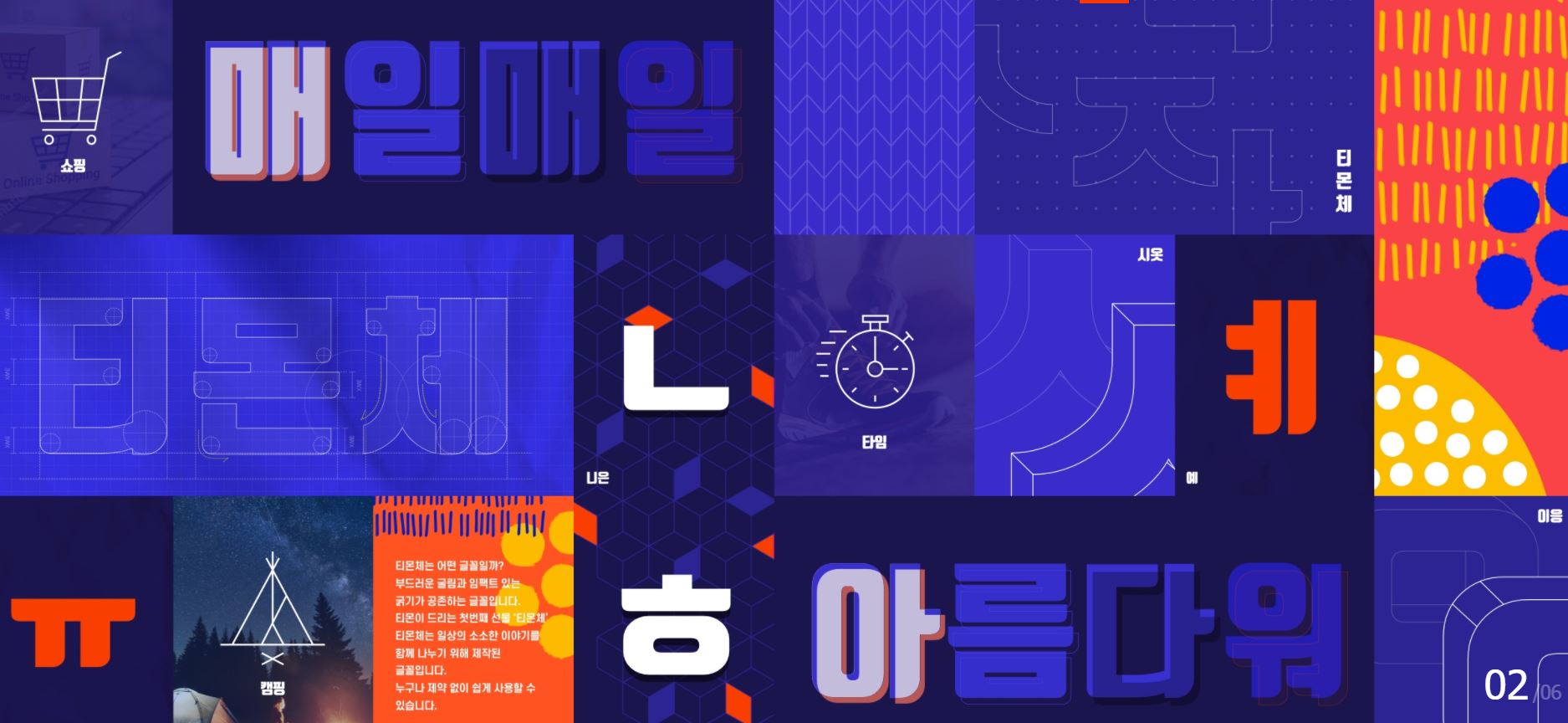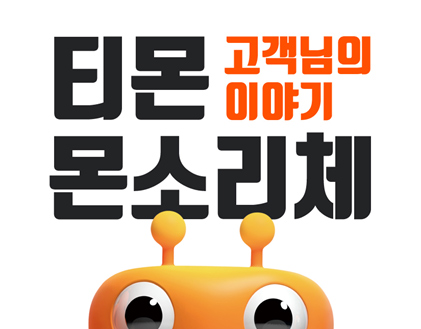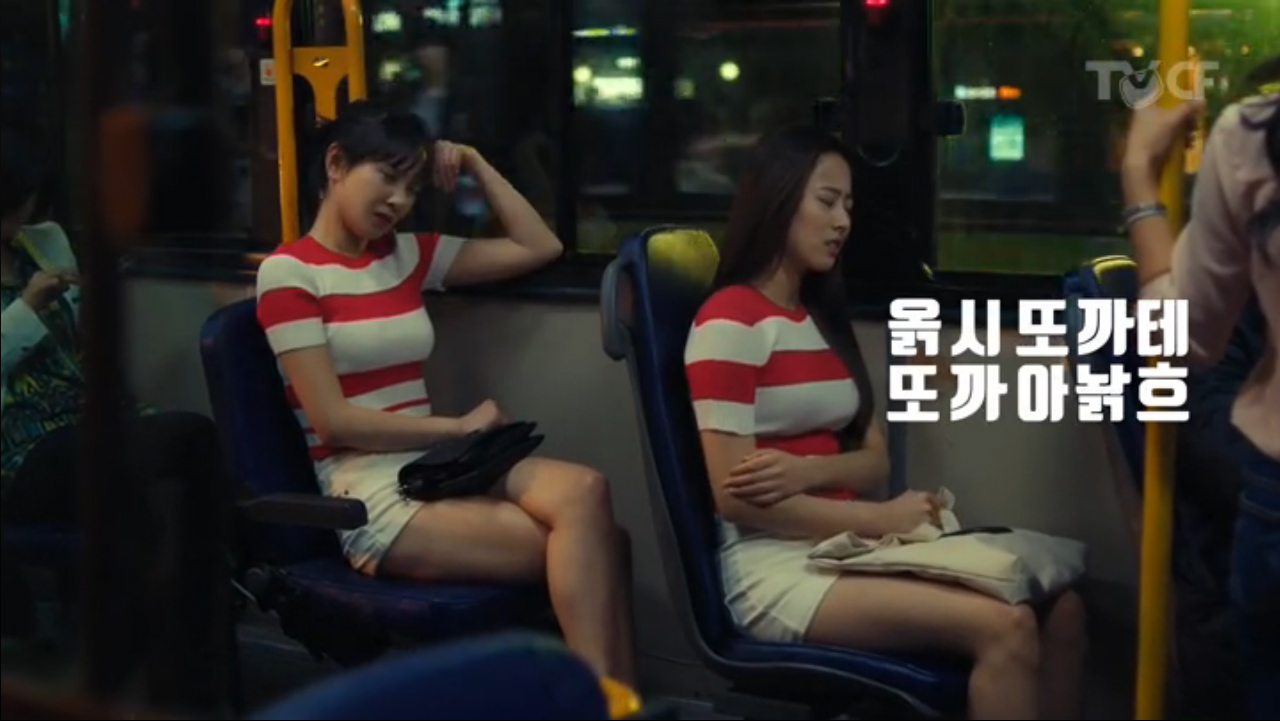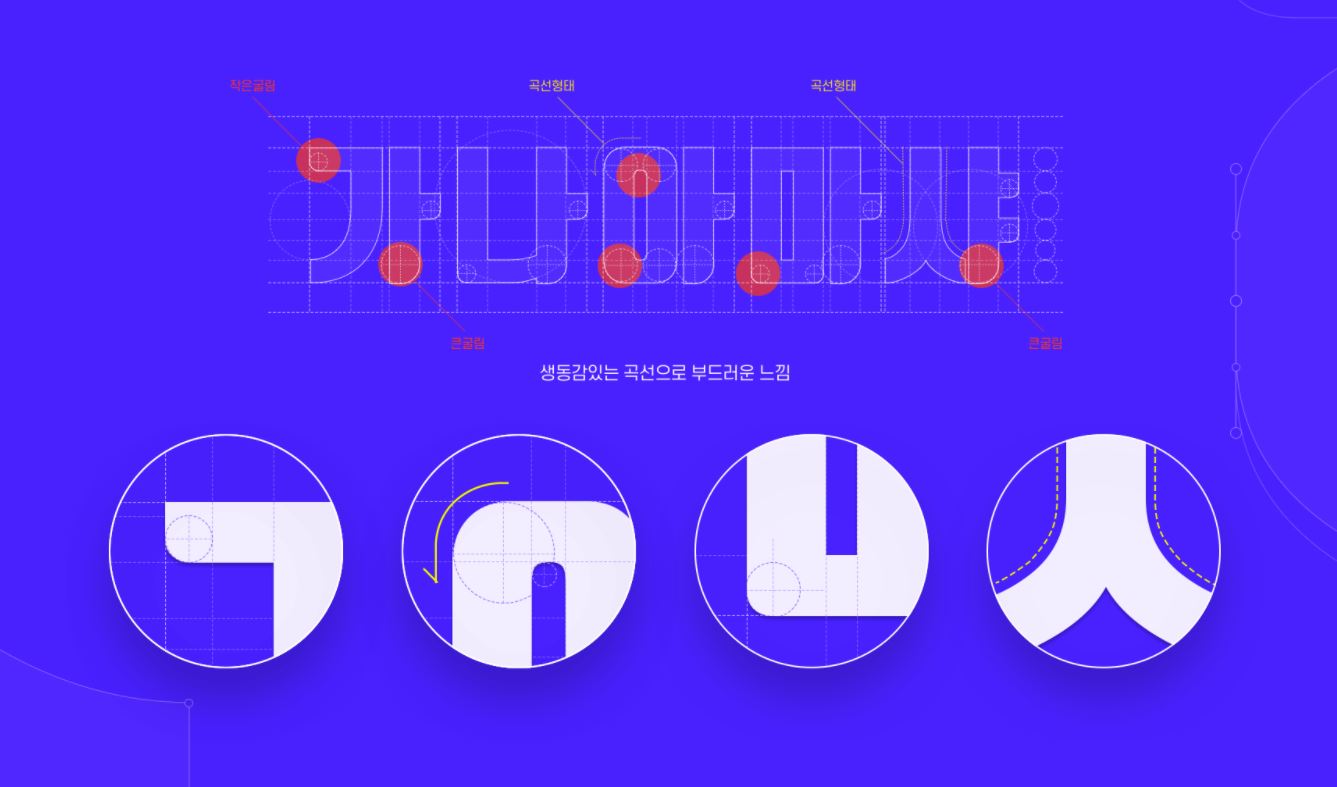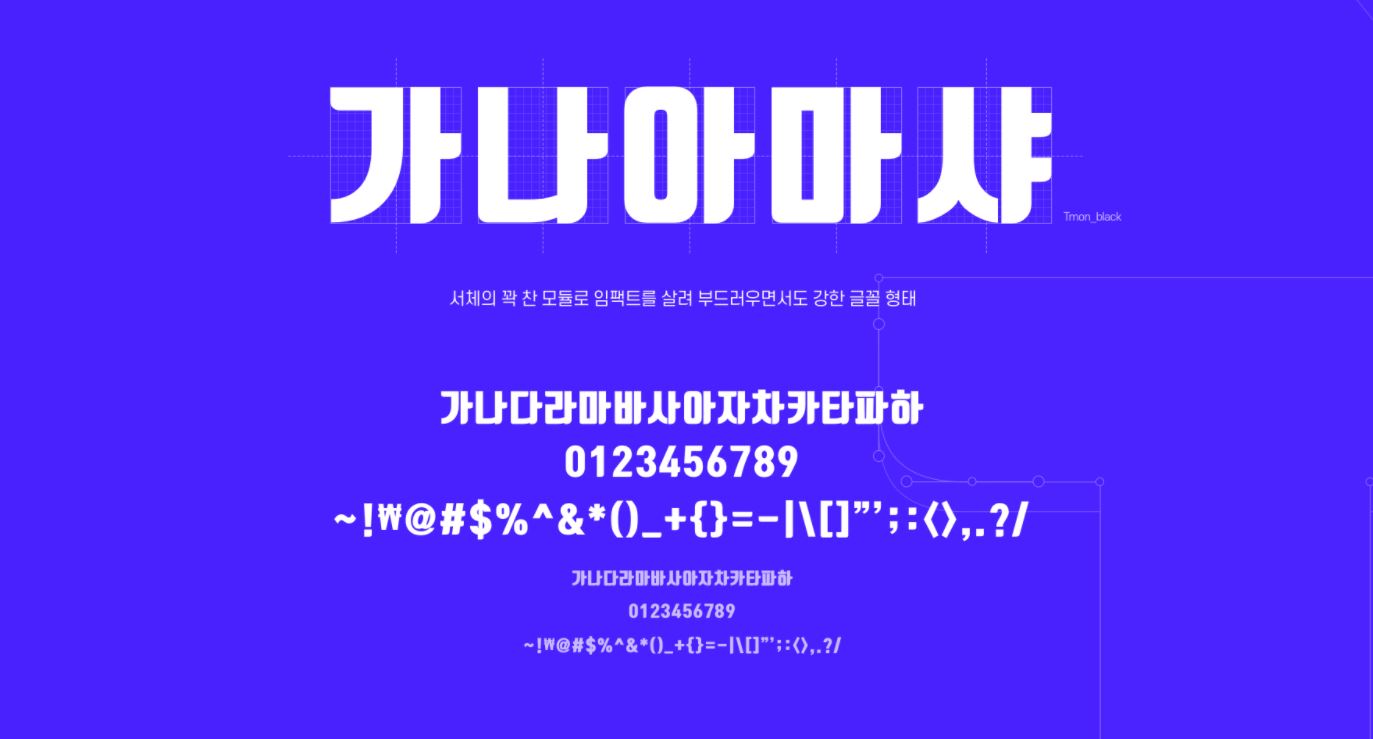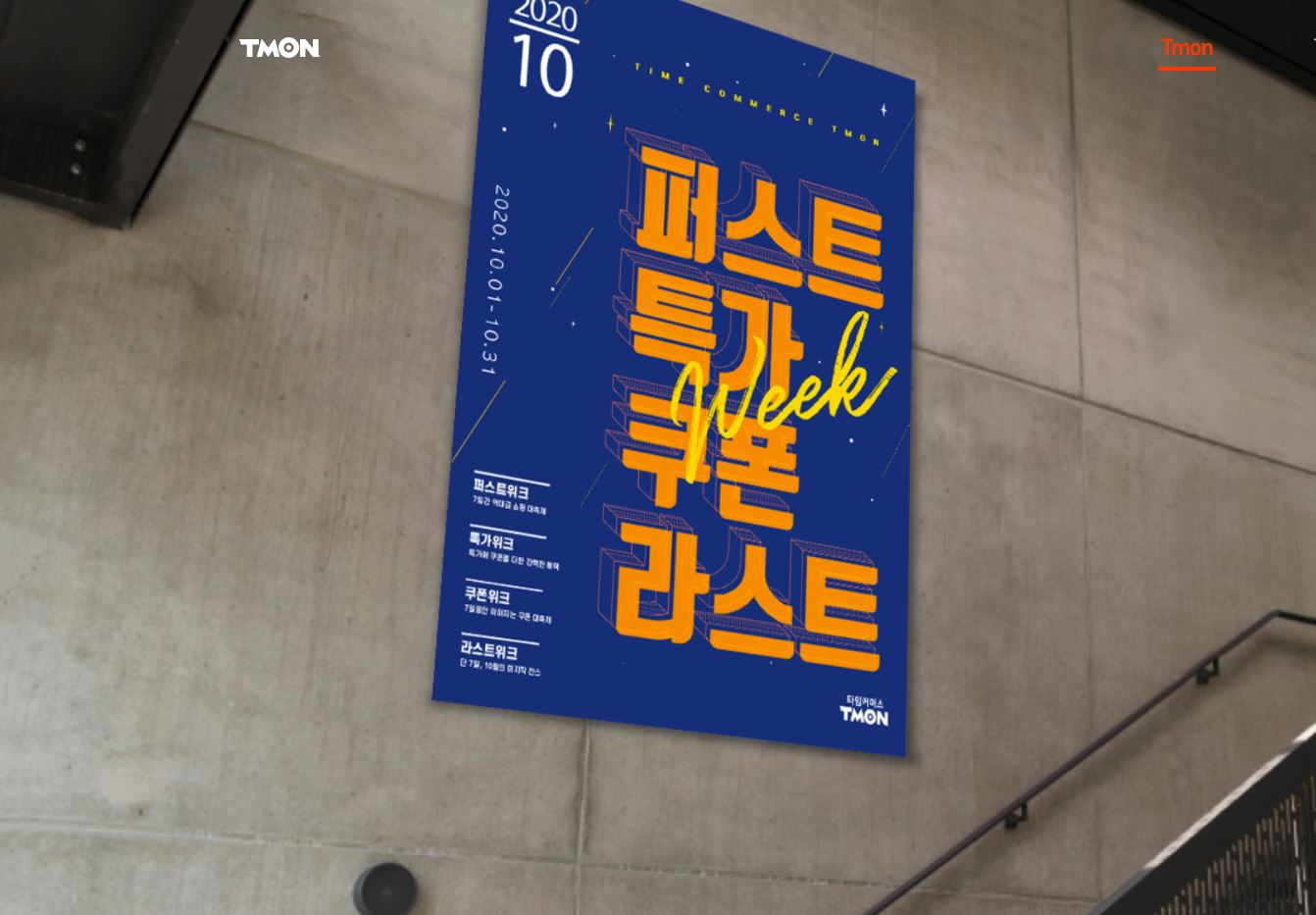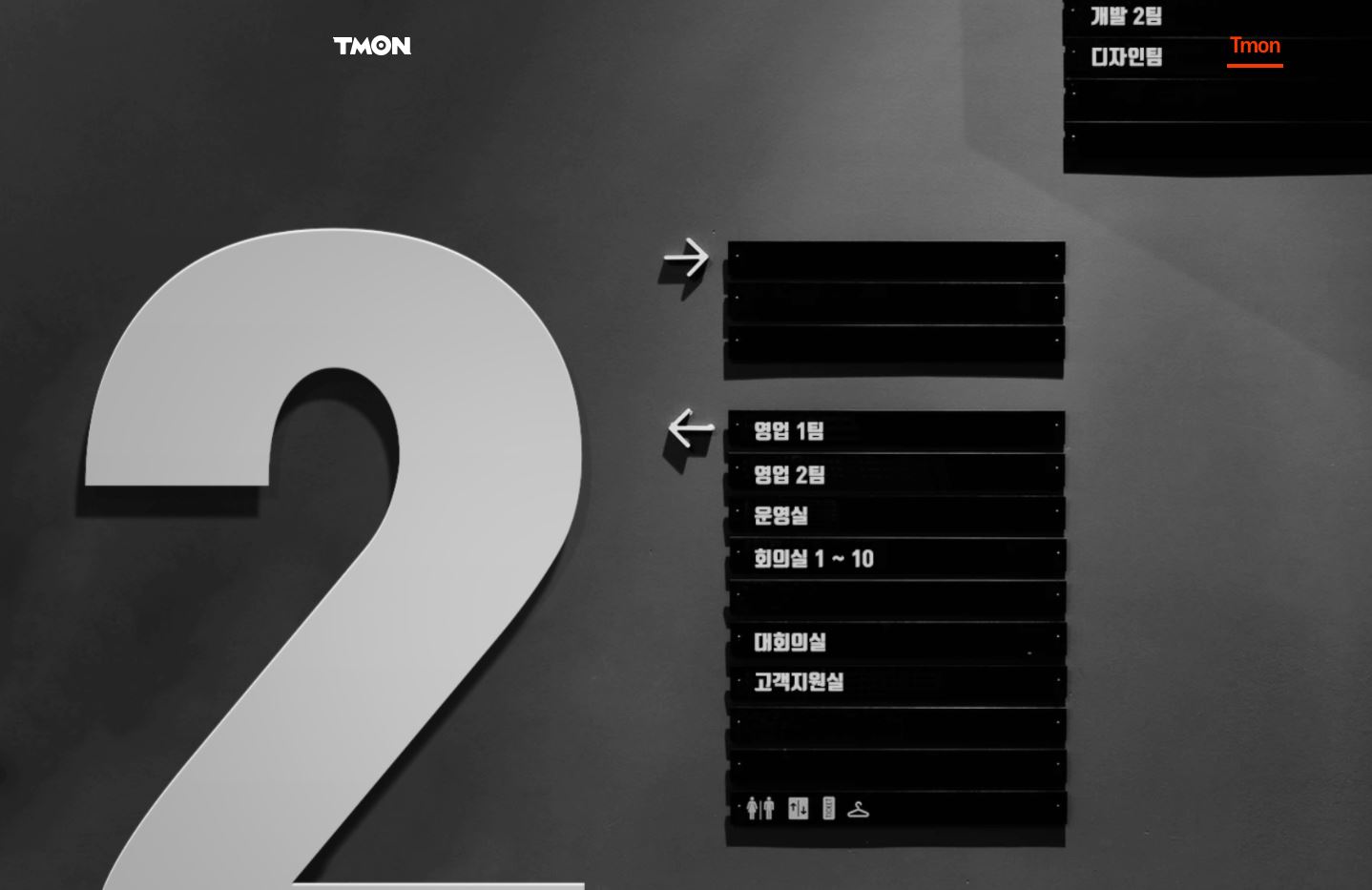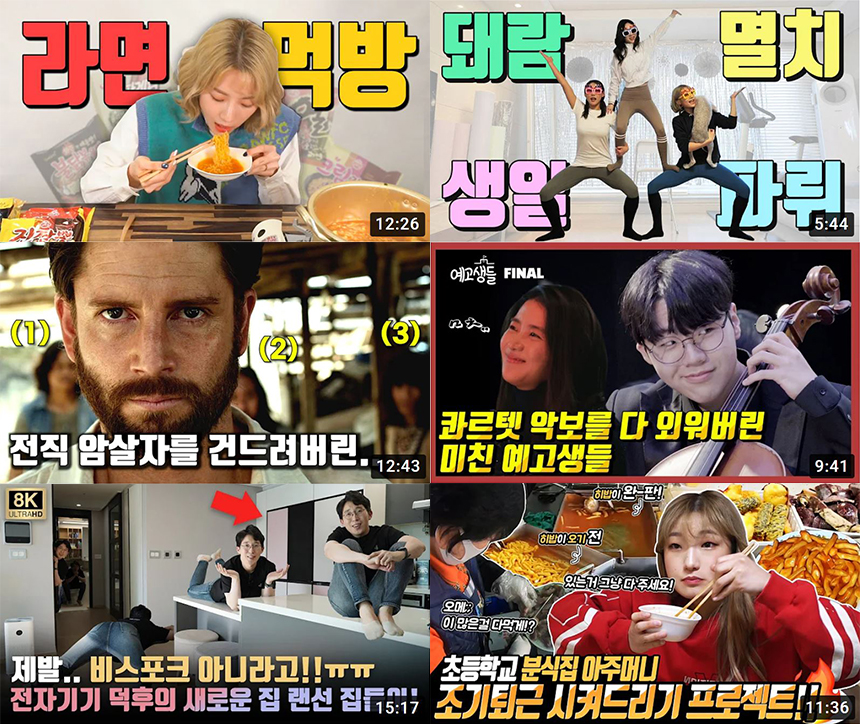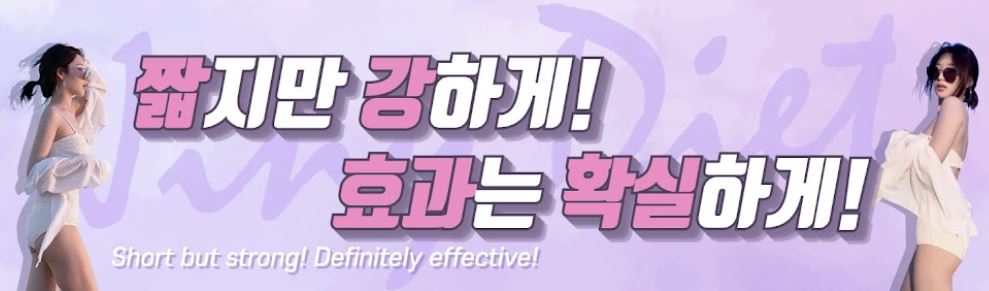
알고 보면 더 좋은 전용서체 이야기! 오늘은 대한민국 소셜 커머스 기업 티몬의 전용서체인 「티몬체」를 소개해 드립니다. RixFont에서 제작한 이 서체는 여전히 다양한 매체에서 가장 많이 사용되고 있는 무료 폰트가 아닐까 싶은데요. 온라인, 오프라인 할 것 없이 현재까지도 많은 사랑을 받고 있는 서체입니다.
티몬체는 2016년 7월, 국내 이커머스 기업 중 가장 먼저 개발 및 배포된 티몬의 기업전용서체입니다. 당시에 소비자들의 웅얼거림, 고객의 소리를 귀담아듣는 티몬이 되겠다는 몬소리 캠페인의 일환으로 제작, '몬소리체'라는 이름으로 처음 세상에 나왔습니다. 2020년 11월, '티몬체'로 글꼴 명칭이 변경되어 현재는 티몬체로 불리고 있습니다.
부드럽지만 강한 제목용 서체
티몬체는 전체적으로 두꺼운 굵기를 가지고 있어 주목성이 높은 제목용 폰트로 제작되었지만 동시에 생동감 있고 부드러운 느낌의 곡선의 형태가 특징입니다. 덕분에 너무 무겁지 않고 캐주얼하면서 간결한 표현이 가능합니다.
서체의 둥근 마무리감이 단순한 고딕 스타일에서는 느끼기 어려운 사랑스럽고 귀여운 느낌을 주기도 하는데요. 이러한 친근한 이미지가 서체와 기업의 이미지를 더욱 긍정적으로 만들어 줍니다.
디자인의 완성은 '폰트' 다.
기업전용서체는 기업의 아이덴티티를 살리면서도 가독성을 놓치지 않아야 하고 기업의 다양한 디자인 작업에도 자연스럽게 어우러져야 합니다. 디자인의 완성은 폰트라는 말도 있듯이 디자인에서 폰트의 역할은 굉장히 큽니다. 아무리 훌륭한 디자인이라도 어울리지 않는 폰트를 썼다가는 멋진 작업을 완전히 망칠 수도 있으니까요. 티몬체는 즐거운 정보를 간결하게 전달하기 좋은 서체인 만큼 디자인적인 활용도가 높습니다.
특가, 할인 행사 포스터나 배너 등 목적이 있는 정보 전달에 특화되어 주목도가 높고, 심플한 표지판, 간판, 로고 등에 사용하기에도 좋습니다. 기본 골격이 단단하고 두껍지만 특유의 부드러움이 친근함을 주기 때문입니다.
#유튜버가_사랑하는_ 무료폰트
유튜브 썸네일에 정말 자주 보이는 폰트 중에 하나인데요. 핫한 유튜버들의 영상 썸네일 폰트로 선택당하고(?) 있는 이 서체가 바로 티몬체입니다. 무료 폰트이기 때문에 접하기 쉬운 이유도 있겠지만, 제작된 지가 꽤 되었는데도 여전히 이렇게 많이 쓰인다는 것은 그만큼 잘 만들어진 서체라서가 아닐까요?
이렇게 오픈 라이선스로 상업적 용도로도 자유롭게 사용이 가능한 착한 폰트 티몬체는 유튜브뿐 아니라 일상생활 속에서도 쉽게 발견할 수 있습니다.
기업전용서체 제작을 통해 브랜드의 정체성을 확립하고, 긍정적이고 친근한 기업의 이미지를 만든 티몬의 사례였습니다. 전용서체를 통한 브랜딩과 커뮤니케이션의 중요성이 갈수록 커지고 폰트의 완성도에 대한 기대감도 점점 높아지고 있습니다. 많은 노력과 시간이 들어가는 전용서체, 브랜딩의 시작입니다.